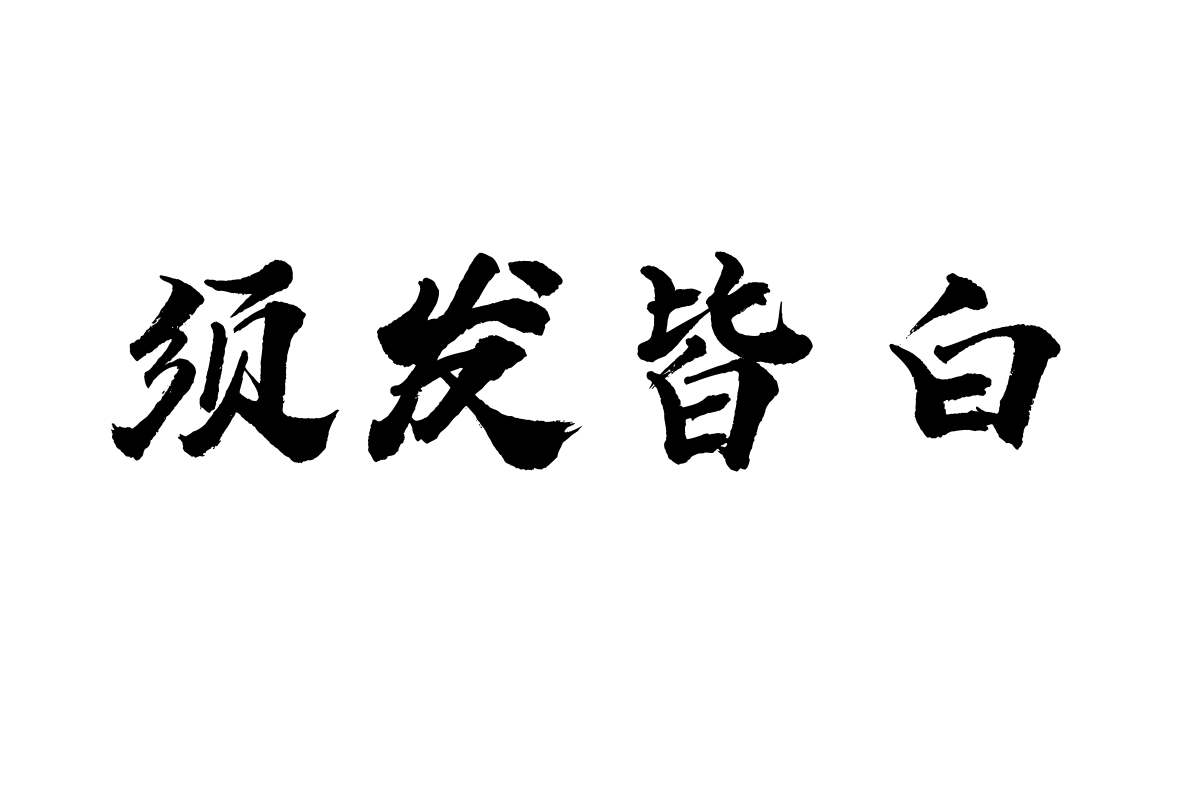
汉标西红市首字体是一款具有独特风格的中文字体,它结合了现代与古典元素,旨在为用户提供一种全新的视觉体验。这款字体的设计灵感来源于中国的传统书法艺术,通过巧妙的字形结构和笔画变化,展现出独特的艺术韵味。
汉标西红市首字体的特点在于其独特的字形结构。它的每个字符都经过精心设计,使得整个字体在视觉上呈现出一种和谐而统一的效果。同时,这种独特的字形结构也使得字体在使用时更加灵活多变,可以适应各种不同的应用场景。
除了独特的字形结构外,汉标西红市首字体还注重笔画的流畅度和美观性。通过精细的笔画处理和合理的间距安排,使得字体在阅读时更加舒适自然。此外,这款字体还具有一定的装饰性,可以通过调整笔画粗细、颜色等参数来达到不同的视觉效果。
总的来说,汉标西红市首字体是一款集现代与传统于一体的中文字体,它以其独特的设计风格和优秀的视觉效果受到了广泛的认可和应用。无论是用于广告设计、书籍排版还是网页制作,这款字体都能为用户带来一种全新的视觉体验。